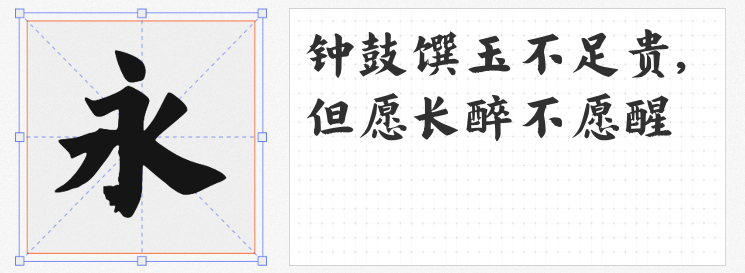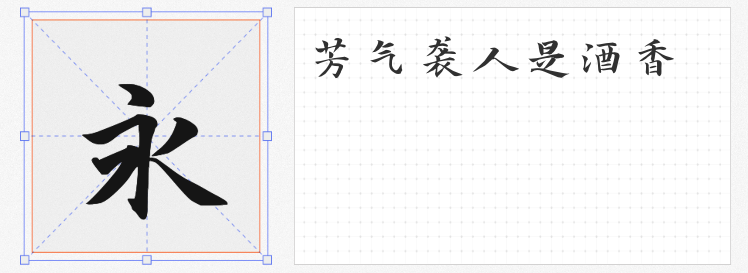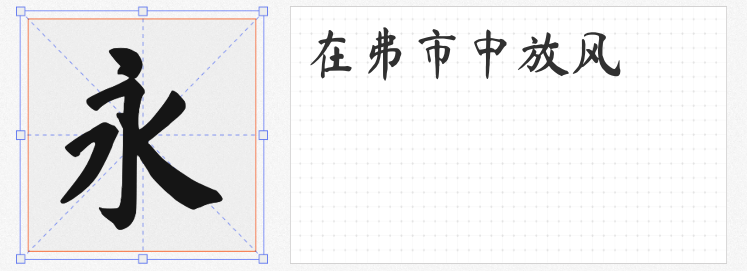
在国风设计席卷全球的当下,书法字体已成为品牌视觉、文化创意与商业传播的核心元素。然而,字体侵权风险始终是设计师的隐忧。本文精选四款兼具艺术价值与法律安全性的免费商用书法字体,涵盖古朴对联体、现代拓展体及创新刻楷风格,为设计注入东方美学灵魂。
基于开源字体「演示春风楷」的拓展字形,寒蝉书体·春秋 春风通过调整西文字符比例、优化字偶间距,解决了原版中英文排版失衡的问题。其笔画粗细过渡自然,竖排时行气连贯,尤其适合文化海报、古籍封面等场景。
以《马善政毛笔楷书》为蓝本,玄冬楷书修复了原版中88个错误字形,新增竖排特性,成为古籍数字化、传统书签设计的首选。其笔画如刀刻斧凿,横画起笔收锋凌厉,竖画中段微曲,模拟毛笔提按效果。
这款源自谷歌开源项目的字体,以“对联体”气质闻名。其笔画粗壮如松,捺画舒展似鹤翼,尤其适合春节营销、寺庙文化宣传。
文岚铭设计出品的程荣光刻楷,模拟木刻版画质感,笔画边缘保留刀痕纹理,横竖画粗细对比强烈,适合品牌LOGO、国潮包装。